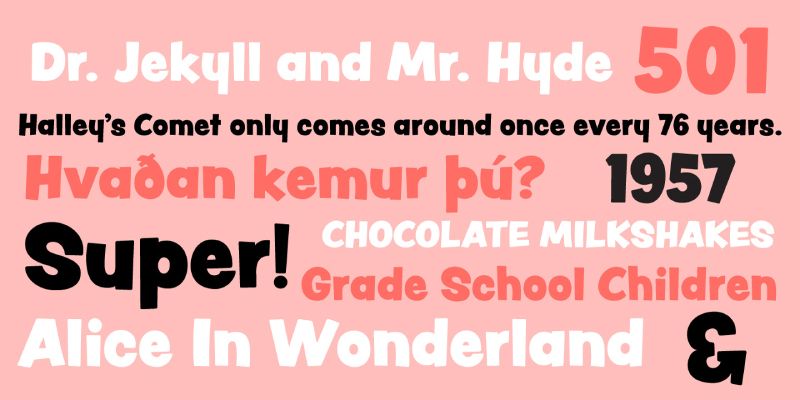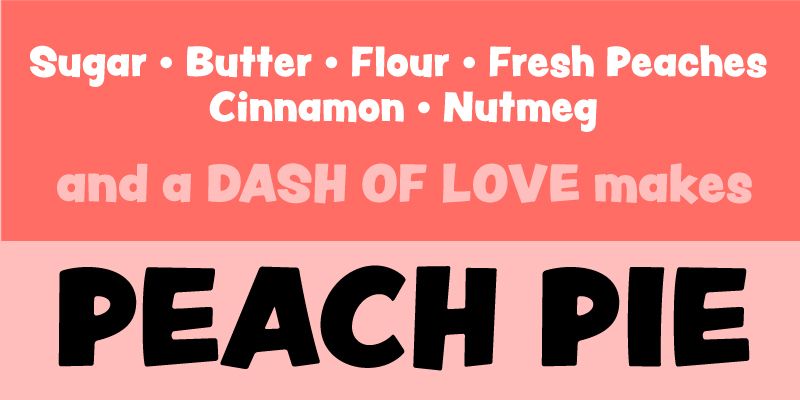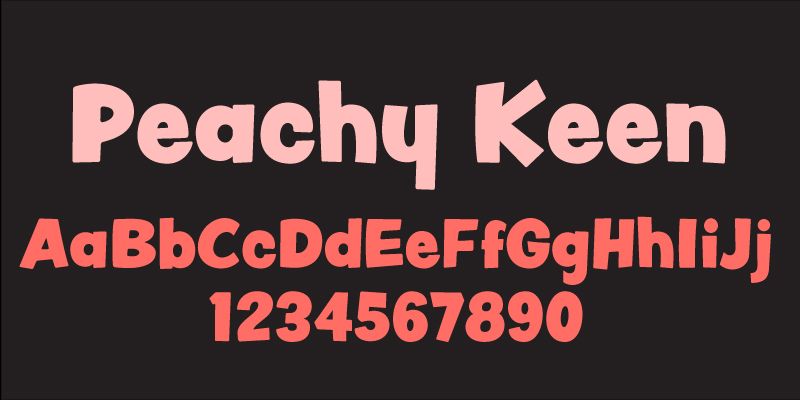
Peachy Keen begrüßt Sie mit kindlicher Unschuld und Spaß. Die verspielten serifenlosen Buchstabenformen sind perfekt für jedes Design, bei dem ein unbeschwertes Gefühl gefragt ist.
Jukebox ist die Erfindung von Jason Walcott, einem langjährigen Schrift-Designer. Walcott entwarf seine erste Schrift mit dem Namen Holiday Times im Herbst 2000 und dies war der Beginn einer langen und wunderbaren Reise zur heutigen Jukebox.
Nach der Entwicklung von fünf oder sechs weiteren Schriften begann Jason im Sommer 2001, seine Schriften auf MyFonts.com zu verkaufen. Zu dieser Zeit wurde sein Schriftanbieter unter dem Namen JAW Fonts gegründet. Einige seiner Designs wurden auf MyFonts.com schnell populär und der Umsatz wuchs bis Ende 2002.
Anfang März 2003 erhielt Walcott einen Anruf von der damals aufstrebenden Veer Inc. Veer war daran interessiert, seine Schriftbibliothek in ihr Angebot aufzunehmen, die damals aus etwa 50 Schriftarten bestand. Aus dem Deal mit Veer entstand ein völlig neues Unternehmen und JAW Fonts wurde im Juni 2003 eingestellt und als Jukebox umgestaltet und neu am Markt eingeführt. Jukebox wurde als exklusives Produkt von Veer von 2003 bis 2015 zu einem der Branchenstandards unter den verfügbaren Typbibliotheken. Jukebox-Schriften wurden auf unzähligen Produkten und Designs, Filmen, Büchern, Fernsehproduktionen und mehr verwendet, von Unternehmen wie Disney, HGTV, The Food Network, Disney Theme Parks, Hershey’s, VistaPrint und vielen anderen. Im Jahr 2011 wurde Walcotts Eloquent-Schriftfamilie unter den „Best of Typeface Design“ im Typography Annual des Communications Arts Magazine genannt.
Am 31. März 2016 schloss Veer seine Türen für immer und die Kuration der Jukebox-Bibliothek ging zurück an Walcott, der es als seine Aufgabe sieht, dafür zu sorgen, dass Jukebox der Designwelt weiterhin hochwertige, professionelle Schrift zur Verfügung stellt.